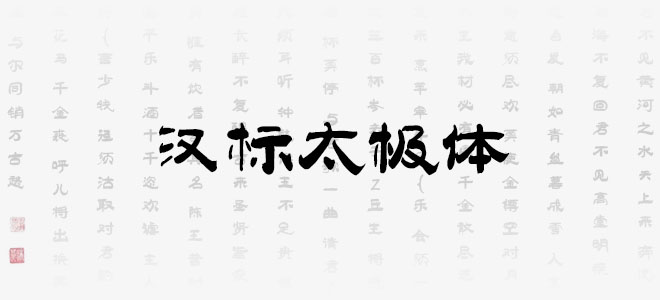
漢標(biāo)太極體在創(chuàng)作時(shí)力求太極元素,端莊平穩(wěn),中正安舒,字體易于識(shí)別、字型規(guī)范而不失特色。行書的運(yùn)筆加入了一些抑揚(yáng)頓挫及個(gè)別筆畫的大舒展,形似人在打太極的感覺。歡迎喜歡漢標(biāo)太極體的朋友前來(lái)下載使用。
漢標(biāo)太極體